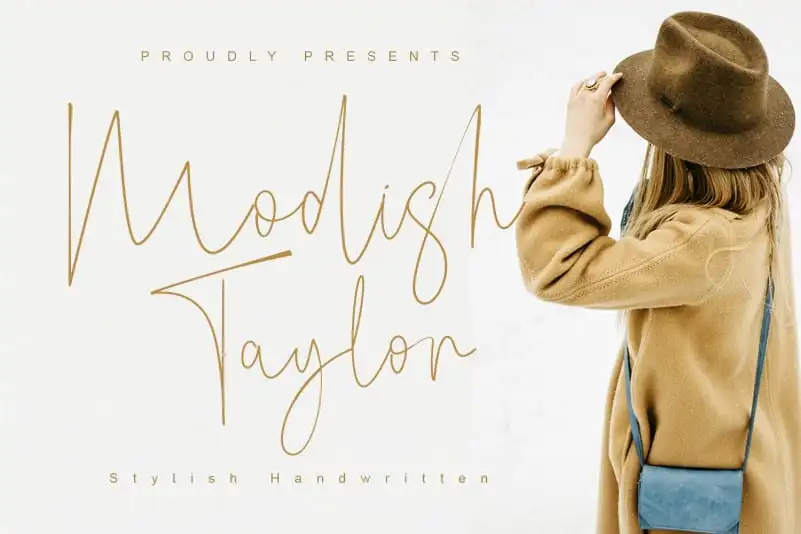
Modish Taylor Handwritten Font – Download Grátis
A Modish Taylor Handwritten Font é uma sugestão perfeita para projetistas buscando adicionar um toque elegante à sua identidade visual. Originada do trabalho meticuloso de um designer chamado Halymunt Studio, esta tipografia script é ideal para trabalhos como branding, logotipos, design de casamentos, postagens nas redes sociais, anúncios e embalagens, além de produtos, etiquetas, fotografia, marca d’água, convites e materiais de correspondência. Seu estilo elegante e minimalista oferece um toque sofisticado a qualquer projeto que exija o sabor da escrita à mão. Com uma visão cuidadosamente elaborada por Halymunt Studio, esta font se destaca em sua categoria de fontes script, tornando-a uma opção versátil para diversos usos e estilos de design.